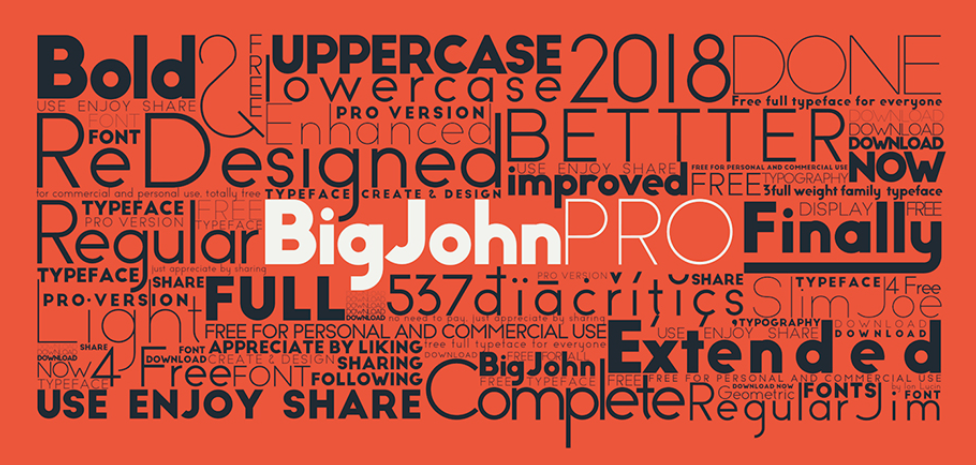
Modern Font Styles
Modern Font là lựa chọn lý tưởng cho những thiết kế cần sự tinh tế và tối giản. Với các đường nét rõ ràng, sắc sảo và thường đi kèm với phong cách sans-serif, font chữ không chân này mang đến sự thanh lịch và dễ đọc trong các dự án từ thiết kế website, thương hiệu, đến in ấn. Hãy cùng khám phá những đặc điểm nổi bật của các phông chữ hiện đại và cách áp dụng chúng để tạo nên các sản phẩm thiết kế ấn tượng.